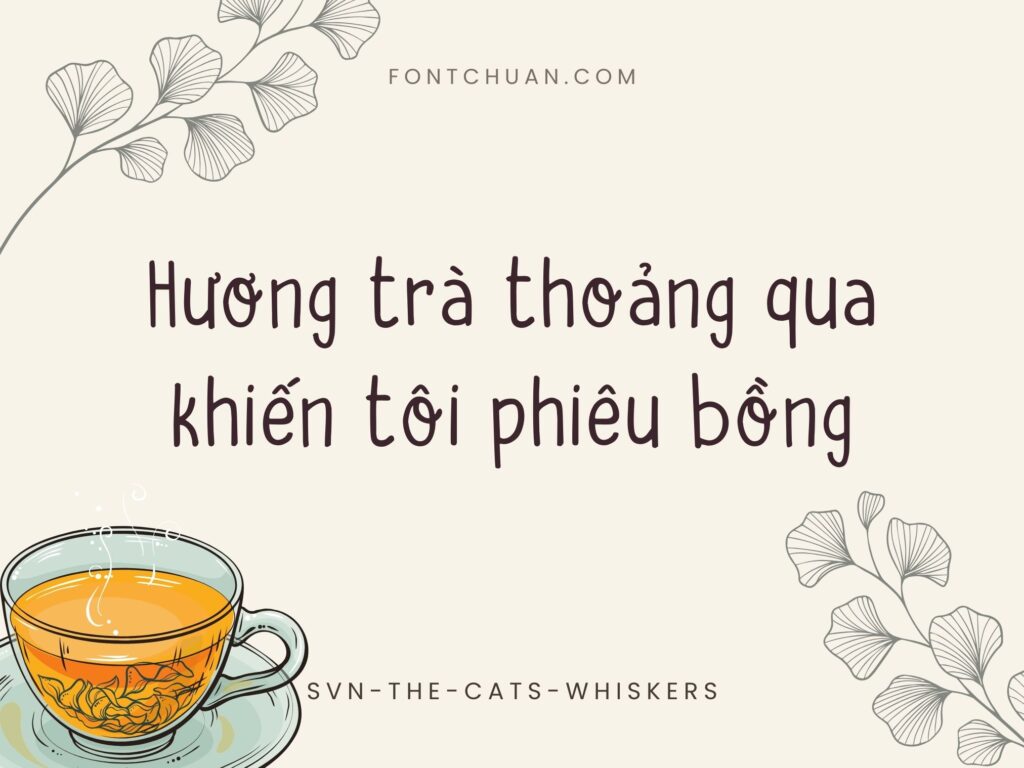
Font SVN The Cat Whiskers Việt Hóa
Tác giả Font: David Kerkhoff
Font SVN The Cat’s Whiskers là phiên bản Việt hóa của kiểu chữ The Cat’s Whiskers, được thực hiện bởi STYLEno.1 Fonts. Đây là một kiểu chữ viết tay ngộ nghĩnh và thân thiện, được thiết kế bởi David Kerkhoff và phát hành qua Hanoded. Với các đường nét uyển chuyển, mềm mại nhưng vẫn giữ được sự ngẫu hứng và gần gũi, font tạo cảm giác như được viết bằng tay thật sự. Bộ font hỗ trợ đa ngôn ngữ và bao gồm đầy đủ ký tự đặc biệt, thích hợp cho nhiều mục đích sử dụng.
SVN The Cat’s Whiskers phù hợp cho các dự án thiết kế cần sự tự nhiên và vui tươi, như thiệp mời, tiêu đề, logo, bài đăng mạng xã hội hoặc thiết kế giáo dục. Các ngành nghề như giáo dục, ẩm thực và spa có thể ứng dụng font để tạo điểm nhấn thân thiện và gần gũi. Ngoài ra, font cũng rất phù hợp cho các sự kiện như Tết, Sinh nhật, Trung thu hoặc các lễ hội khác.